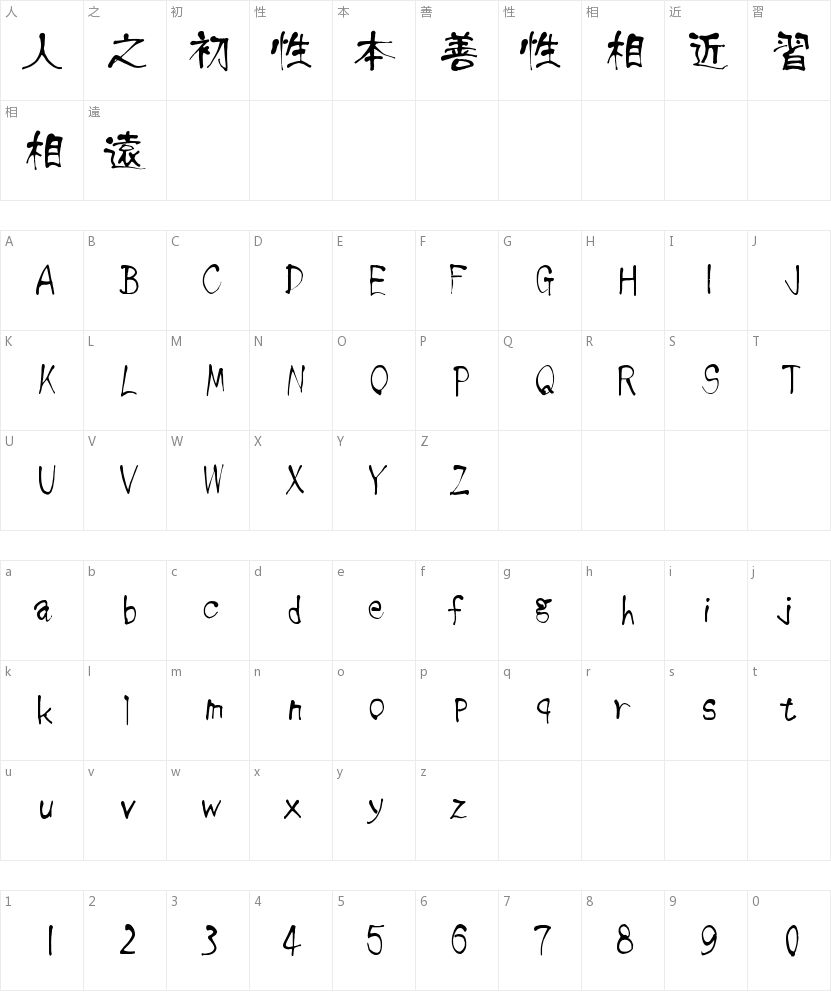
白舟唐草书法
白舟唐草书法,又称“白舟草书”,是中国古代唐代书法家白舟派创立的一种书法。白舟唐草书法以唐代白居易的草书为基础,以其个人的书法特色为主体,并融合了唐代书法家的书法特色,形成了其独特的书法风格。白舟唐草书法的字体特点是楷书结构,笔画粗细相间,笔画流畅,笔画有力,笔法厚重,笔触清晰,构图简洁,富有节奏感。白舟唐草书法被誉为“中国古代书法的精华”,是中国古代书法的代表作。
白舟唐草书法是一款非常不错的手写艺术字体,具有很好的视觉感,适合于文化类的宣传设计、商业类品牌的广告和产品包装设计以及个性化文字排版等较多场景。